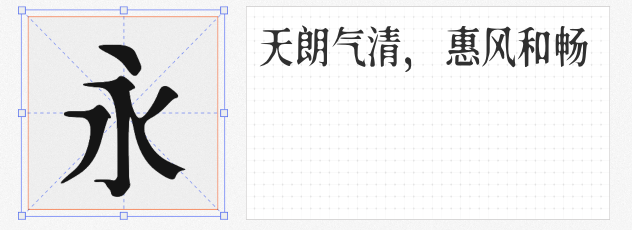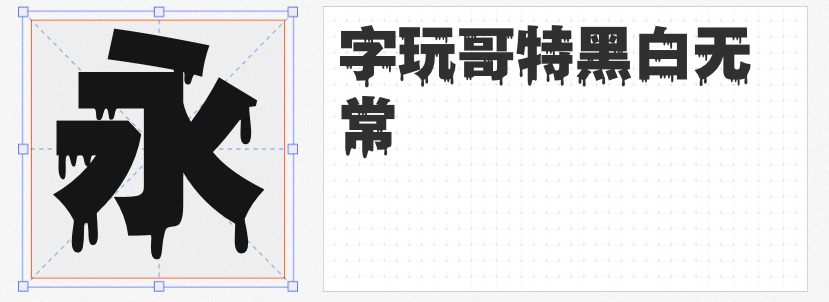
万圣节将至,如何用字体为设计注入诡异、神秘的气息?以下四款免费商用字体,以独特的视觉风格和细节处理,完美适配节日主题的创意需求,助你轻松打造令人过目难忘的惊悚视觉。
这款字体以经典哥特风格为基调,融入不规则血滴元素,瞬间营造出阴森、诡异的氛围。笔画粗黑有力,棱角分明,搭配滴落的“血迹”装饰,仿佛从恐怖游戏中跃然而出。无论是海报标题、派对邀请函,还是社交媒体配图,它都能强化视觉冲击力,让设计充满压迫感与紧张感。
基于思源宋体改造的新愚公沧桑体,通过随机扭曲效果模拟出被时间侵蚀的质感。笔画边缘的模糊与变形,仿佛古老墓碑上的刻字,或废弃城堡中的残破标语。这种“不完美”的设计,恰好契合万圣节中“腐朽”“神秘”的主题,适合用于背景文字、道具标签或氛围装饰,增添细节层次。
得意黑以80年代手绘美术字为灵感,窄长的字身与瘦高的字面赋予它独特的优雅与诡异平衡。斜体设计自带动态感,仿佛文字在黑暗中摇曳飘动。虽不直接表现恐怖,但其复古气质与隐约的不安感,非常适合万圣节派对海报、复古风格插画中的标题或短句,营造“优雅而危险”的视觉氛围。
看似可爱的圆润字体,实则暗藏玄机。黄油体将直角转化为圆角,笔划简洁但细节考究,部首的45°缺角设计既提升阅读性,又隐约透出机械感。这种“柔软与坚硬”的矛盾,可巧妙用于万圣节主题的儿童派对设计(如南瓜灯、糖果包装),或反差感海报——用圆润字体呈现恐怖标语,制造意外惊喜。
从哥特血滴到岁月斑驳,从复古斜体到圆润反差,这四款字体以不同风格诠释万圣节的“惊悚美学”。它们均支持免费商用,设计师可放心用于海报、装饰、社交媒体等场景,为节日创意增添独特魅力。这个万圣节,让字体成为你的“设计魔法”!